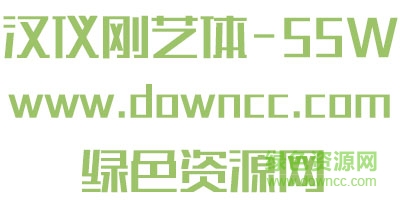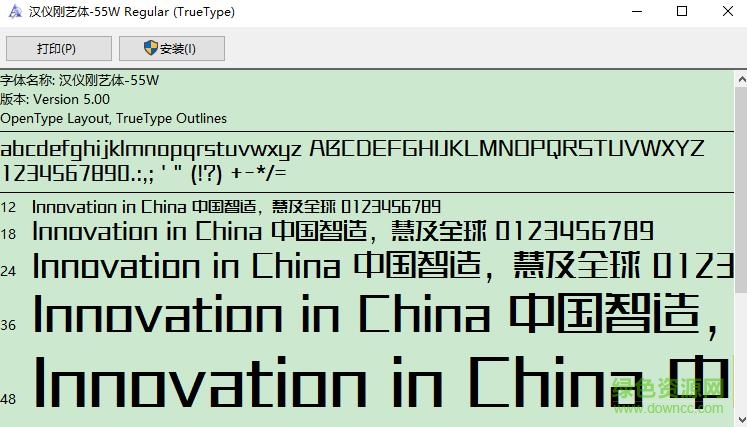
漢儀剛藝體 55簡/繁
漢儀剛藝體 55
漢儀剛藝體-55W字體特色
【蒼勁古樸】
字體樸素無華,飽含古時之風韻,能帶給人們一種懷舊感覺,這種個性的字體適用于傳統(tǒng)產(chǎn)品,民間藝術(shù)品等主題。
【穩(wěn)重挺拔】
字體造型規(guī)整,富于力度,給人以簡潔爽朗的現(xiàn)代感,有較強的視覺沖擊力,這種個性的字體,適合于機械科技等主題。
【活潑有趣】
字體造型生動活潑,有鮮明的節(jié)奏韻律感,色彩豐富明快,給人以生機盎然的感受。這種個性的字體適用于兒童用品、運動休閑、時尚產(chǎn)品等主題